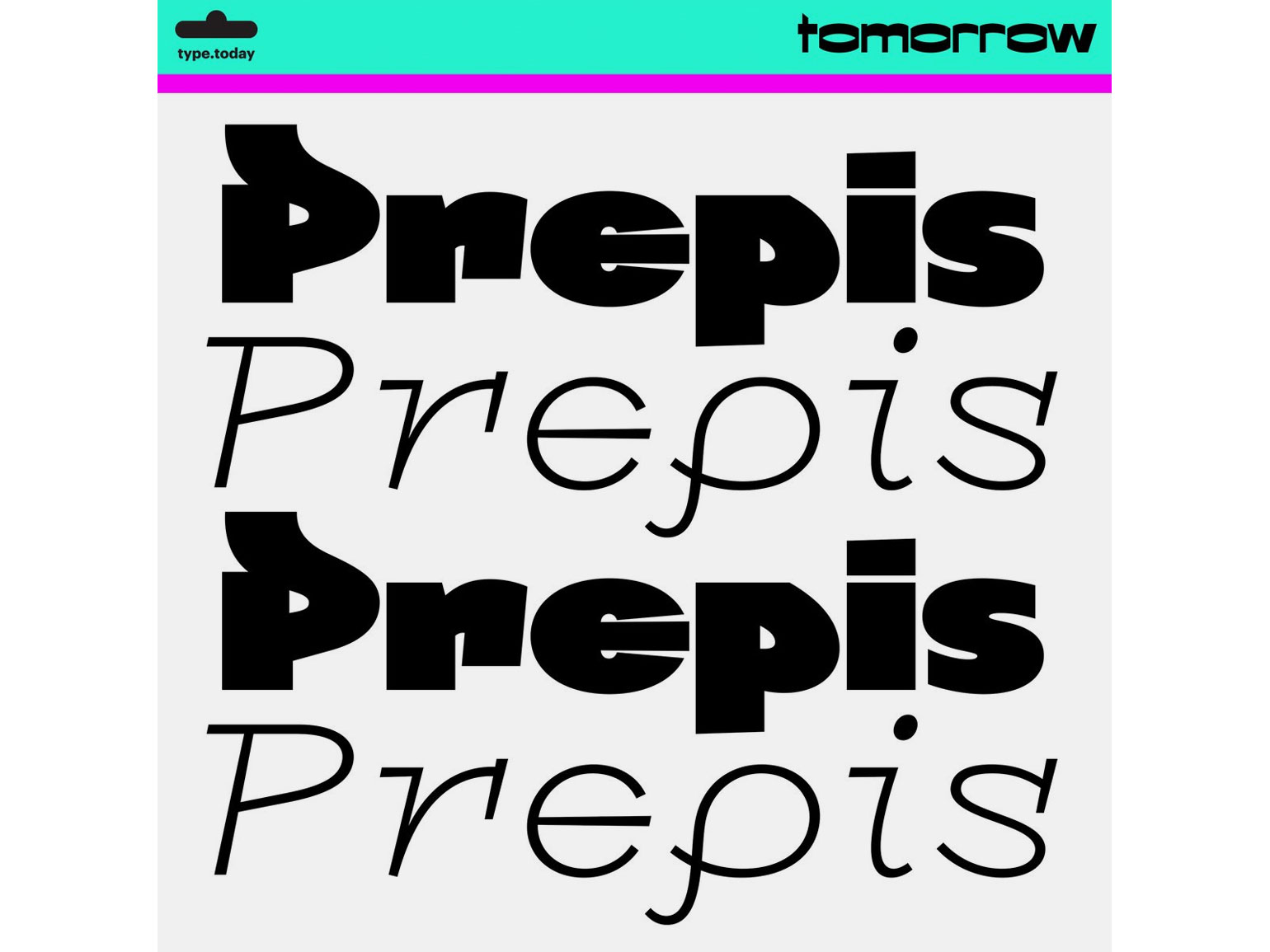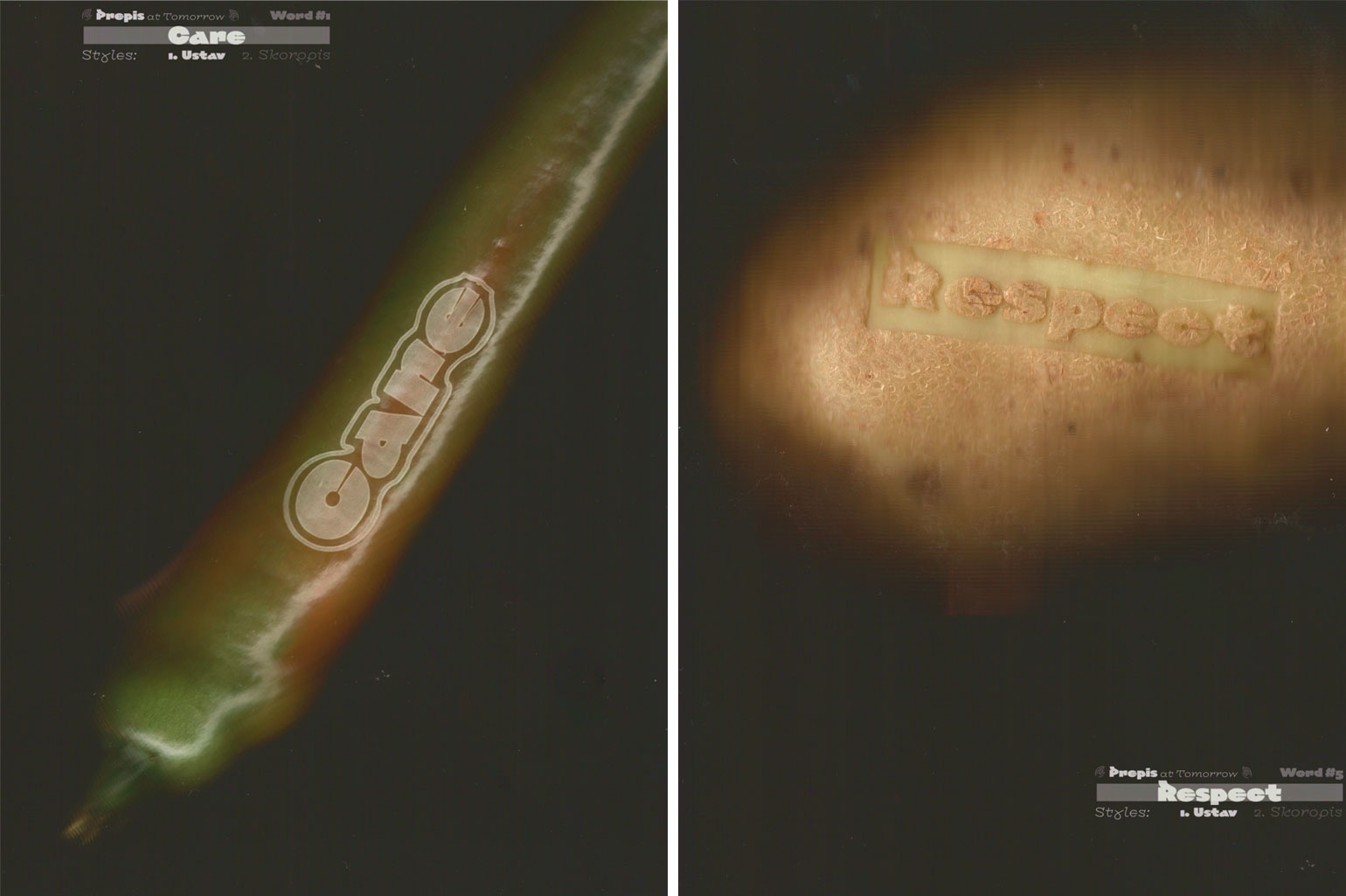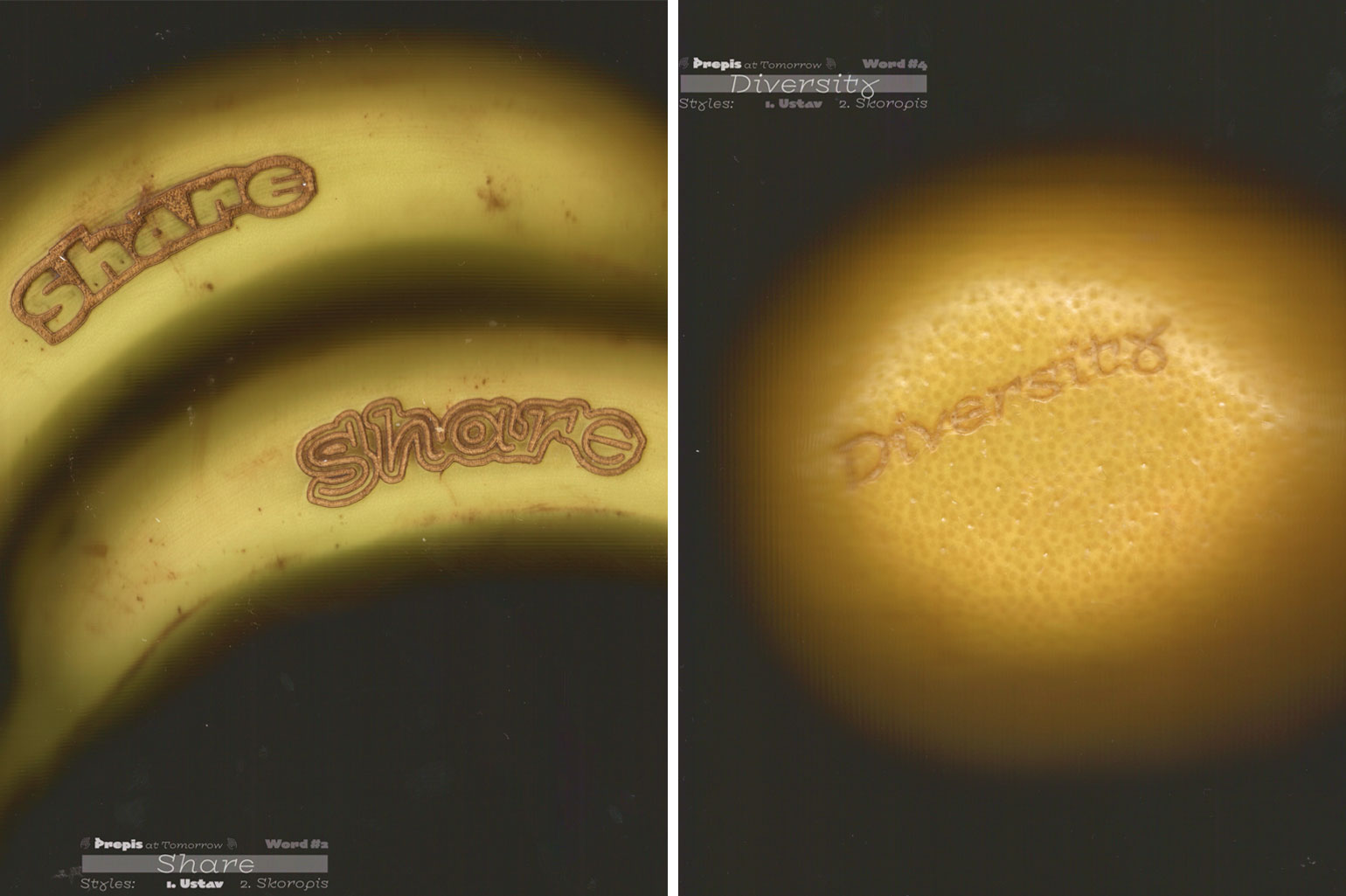
Дизайнер Любослав Боянов представил новый шрифт Prepis
Это современное переосмысление кириллической традиции.
Болгарский шрифтовой дизайнер и каллиграф Любослав Боянов выпустил новый шрифт Prepis — дипломный проект, созданный в рамках магистерской программы TypeMedia в Королевской академии искусств в Гааге (KABK). При создании этого шрифта автор вдохновился средневековыми кириллическими манускриптами.
По замыслу Боянова, Prepis стремится «переприсвоить» исторические кириллические стили — устав и скоропись, которые в последние годы нередко оказывались в поле националистической и ультраправой визуальной риторики. Несмотря на глубокие исторические корни, шрифт задуман как свежий и оптимистичный. Предполагается, что он способен вернуть уставу и скорописи жизнь в нейтральных и позитивных культурных контекстах.
В семейство входят два начертания — Skoropis и Ustav. Шрифт поддерживает контекстуальные лигатуры и набор стилистических альтернатив, а также работает с широким списком языков, включая русский, украинский, болгарский, сербский, белорусский и большинство европейских языков на латинице. Для знакомства с гарнитурой доступна бесплатная пробная версия.
Любослав Боянов — выпускник Болгарской высшей школы искусств и Национальной художественной академии, где он сосредоточился на шрифтовом дизайне. После обучения в Нидерландах дизайнер вернулся в Софию, где продолжает сотрудничать со студией Type Forward и работает над диссертацией, посвящённой типографике как форме культурного производства.